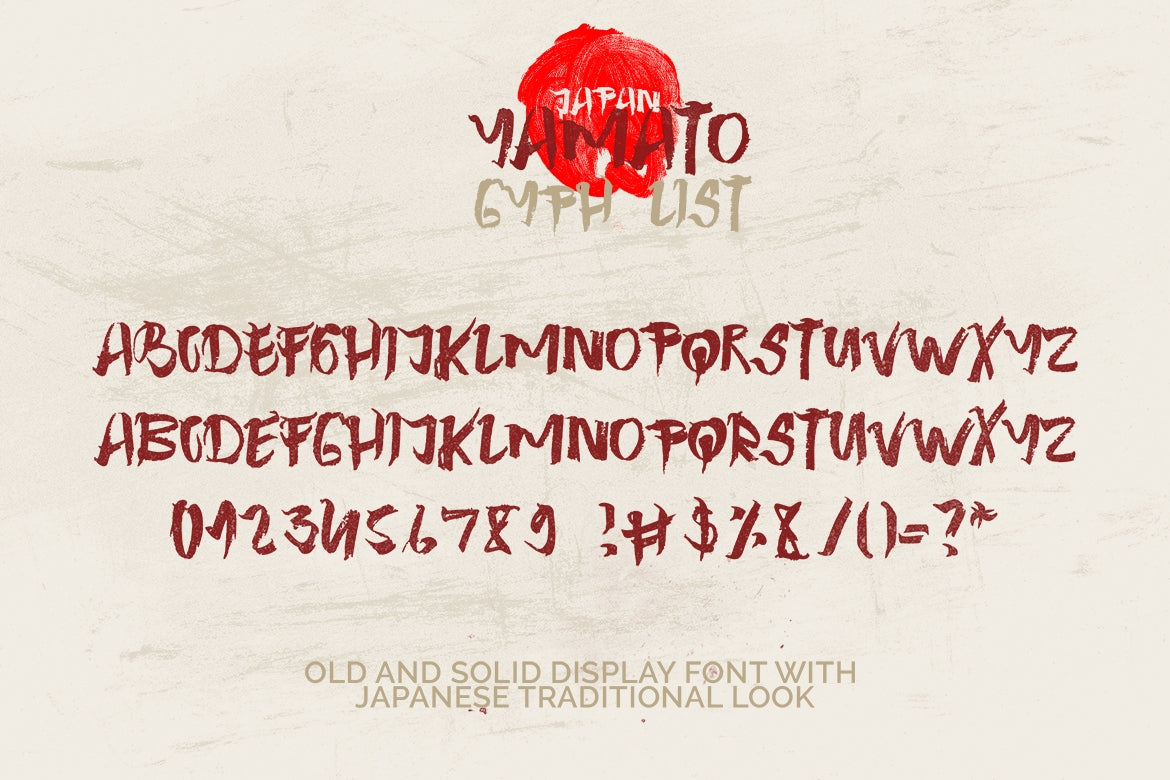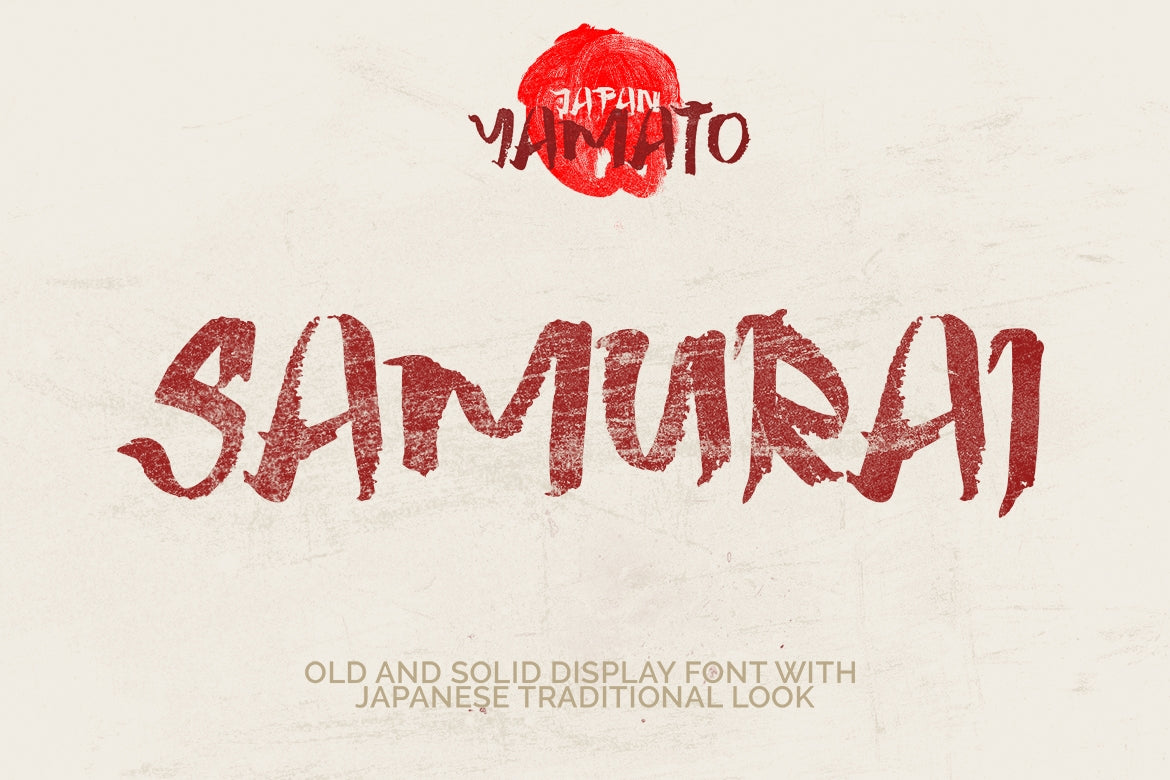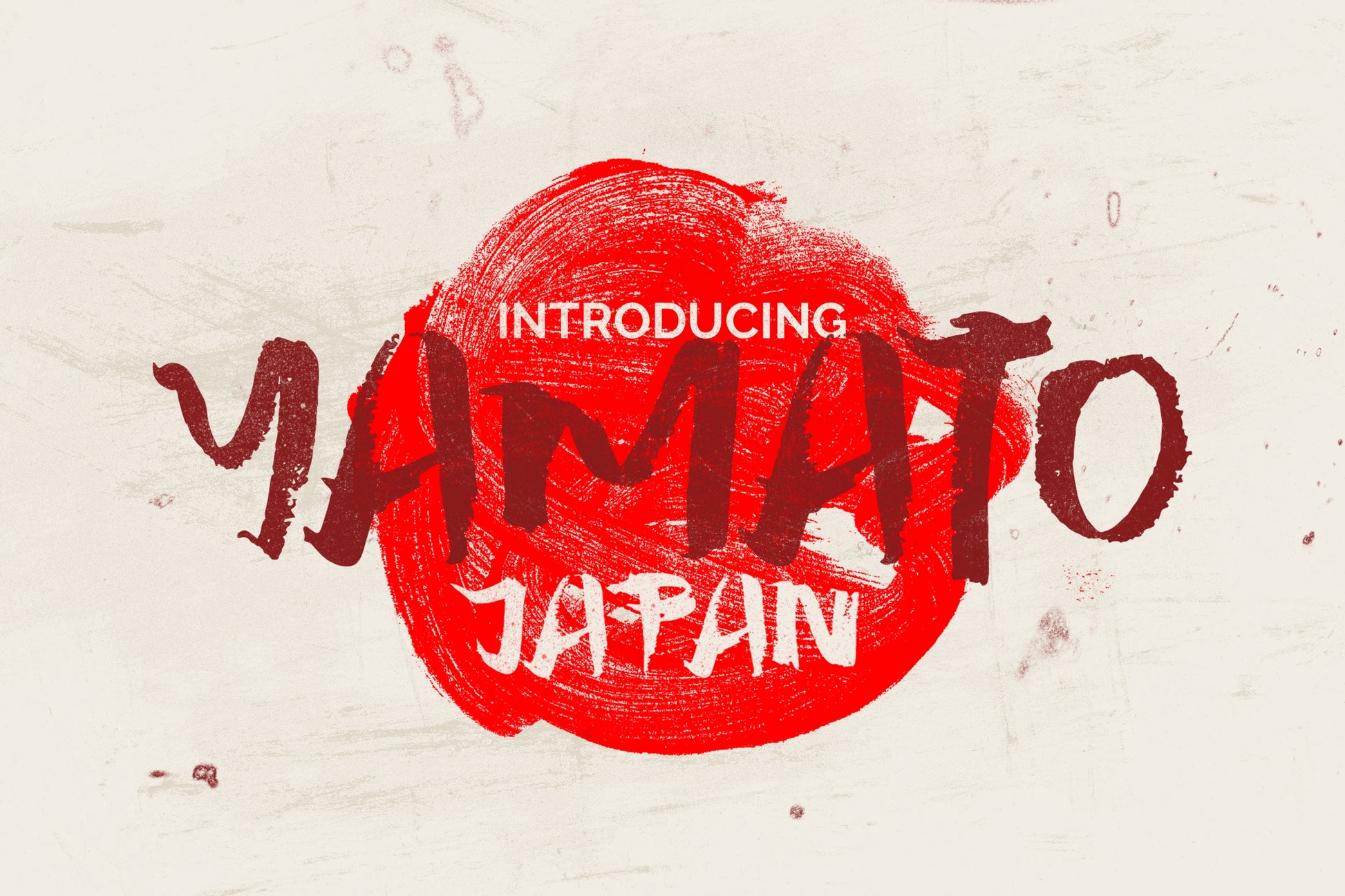
ヤマトフォント
Yamato Japan は、日本の伝統的な感覚からインスピレーションを得た、大胆で荒々しいディスプレイフォントで、日本のあらゆるイベントに適しています。
また、さまざまな文字や合字を組み合わせて使用​​することで、楽しみながら独自のスタイルを作り出すことができます。
このフォントを使用すると、さまざまな文字、代替文字、合字を自由に使用して組み合わせることができるため、デザインやあらゆる種類のプロジェクトがユニークな傑作になることが保証されます。
• このフォントには基本的なラテン語の発音区別記号が含まれています。
フォントには次の多言語サポートが含まれています。 č ć ž š Č Ć Ž Š ä ö ü Ä Ö Ü ß ¿ ¡